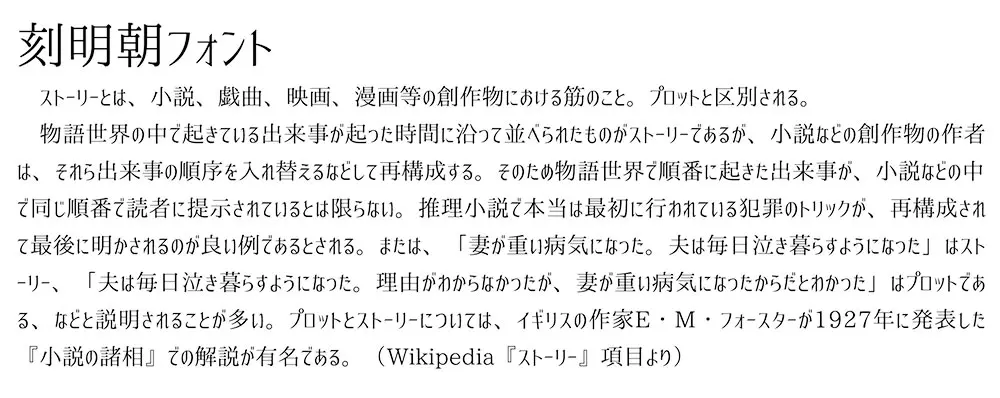
刻明朝是一種通過將極小的平假名和片假名與普通明朝漢字字體相結合而創建的字體。與平假名和片假名原本柔軟自然的形狀形成對比,其特點之一是人工和略帶機械的“硬度”。至於假名字符,單槓像漢字一樣筆直地延伸到側面,並且具有相似的刻度。豎條也不同,裝飾類似於字母的線條。它正是一種具有漢字字體和字母字體融合的假名字符的字體。
平假名和片假名具有獨特的元素,但並不誇張,並以沉穩的設計完成。曲線流暢地改變粗細,給人一種優雅浪漫的印象。該設計與假名字符的原始骨架相去甚遠,但它具有遵循每個字符的面部表情的禮貌骨架,因此不影響可讀性。